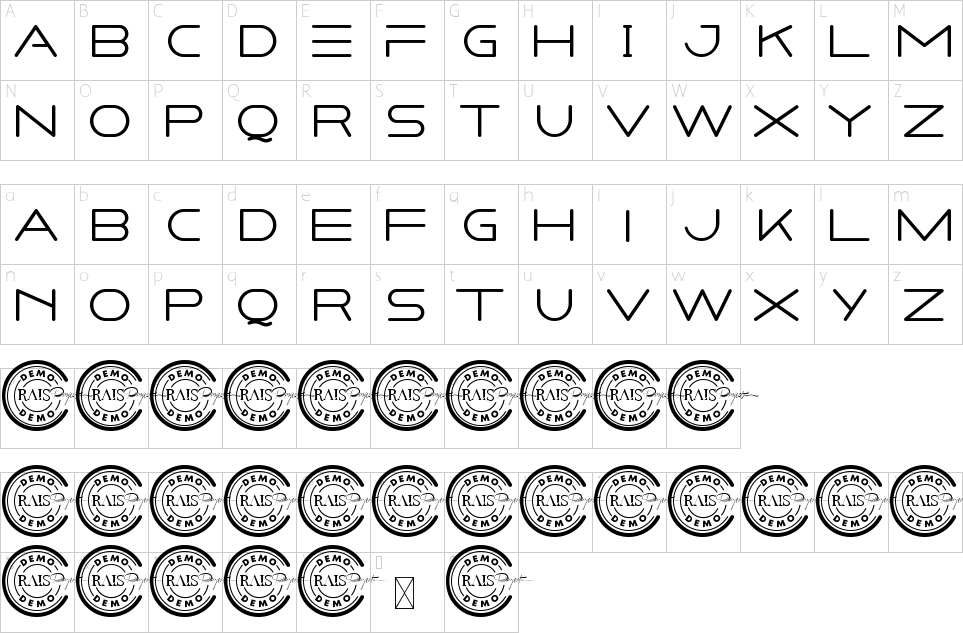
Damention Font – Fonte Grátis
Damention Font
A Damention Font é uma elegante opção para designers que buscam adicionar um toque único a seus projetos digitais. Desenvolvida por raisproject, essa fonte foi projetada com cuidado para oferecer um equilíbrio perfeito entre legibilidade e estilo moderno. É especialmente adequada para uso em sites de design pessoal, editoriais digitais ou até mesmo como uma fonte de escrita em documentos profissionais. Conhecida por sua simetria e beleza geométrica, a Damention Font é uma escolha excelente tanto para quem busca arquitetar um layout minimalista quanto para aqueles que desejam introduzir elementos mais elaborados. Aproveite esta fonte gratuita para explorar seus possíveis na composição de textos e gráficos digitais em seu próximo projeto. Com apenas 1,962 downloads, é uma opção sólida para designers de todas as idades buscando qualidade e versatilidade em sua biblioteca de fontes. Descubra por si mesmo a potência da Damention Font e deixe sua marca única em cada criação.
Mapa de caracteres da fonte Damention Font